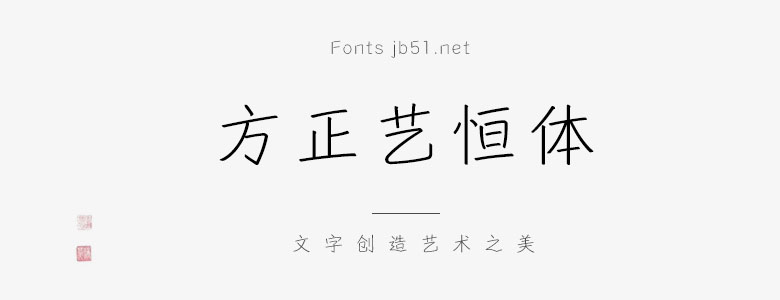
方正藝恒體家族由方正字庫(kù)郭炳權(quán)設(shè)計(jì)師出品的藝術(shù)字體,字體以時(shí)代手寫體的風(fēng)格結(jié)合傳統(tǒng)楷書的造型,使該字體充滿自然自在的藝術(shù)氣質(zhì),適合應(yīng)用于藝術(shù)設(shè)計(jì)、平面宣傳設(shè)計(jì)、網(wǎng)頁(yè)設(shè)計(jì),書法等領(lǐng)域。
方正藝恒體以時(shí)代手寫體的風(fēng)格結(jié)合傳統(tǒng)楷書的造型,使該字體充滿自然自在的藝術(shù)氣質(zhì),適合酒類、咖啡、茶葉及男士用品品牌的宣傳。。